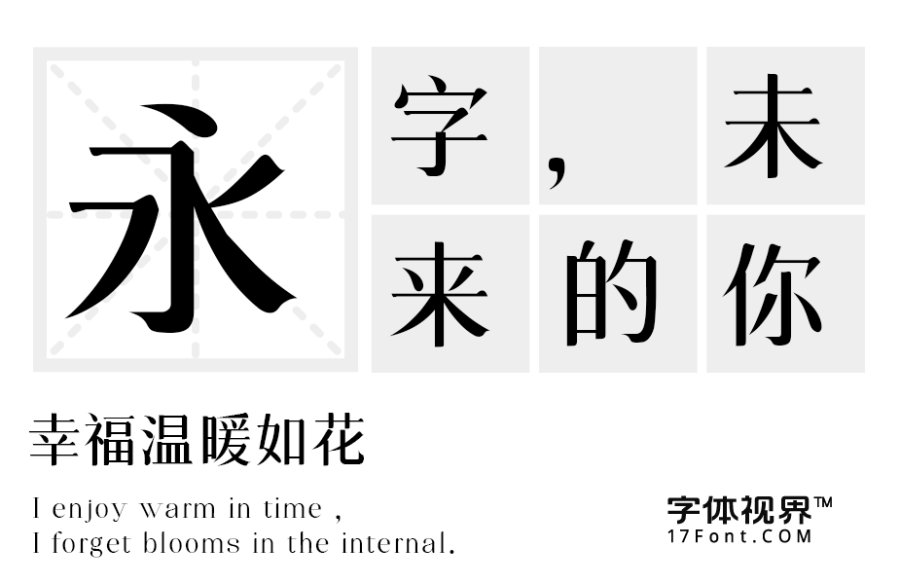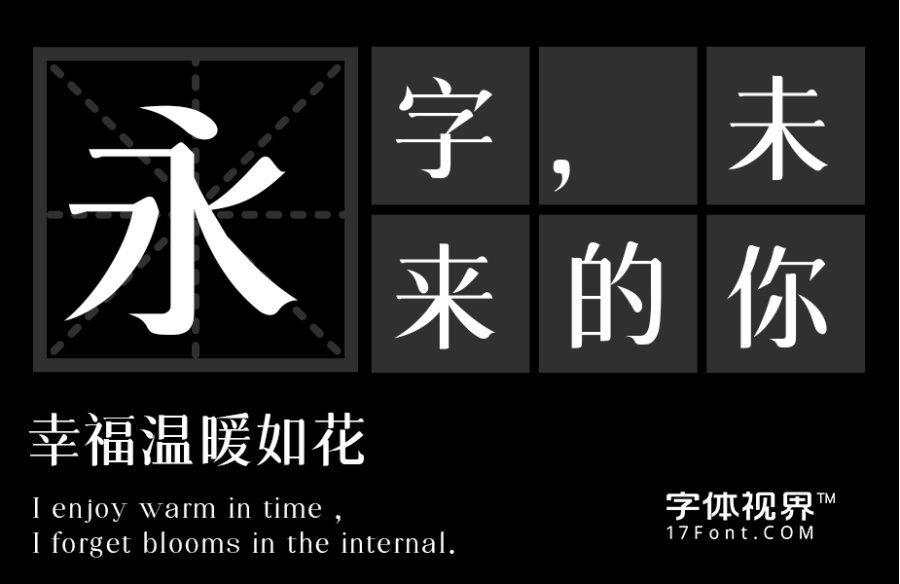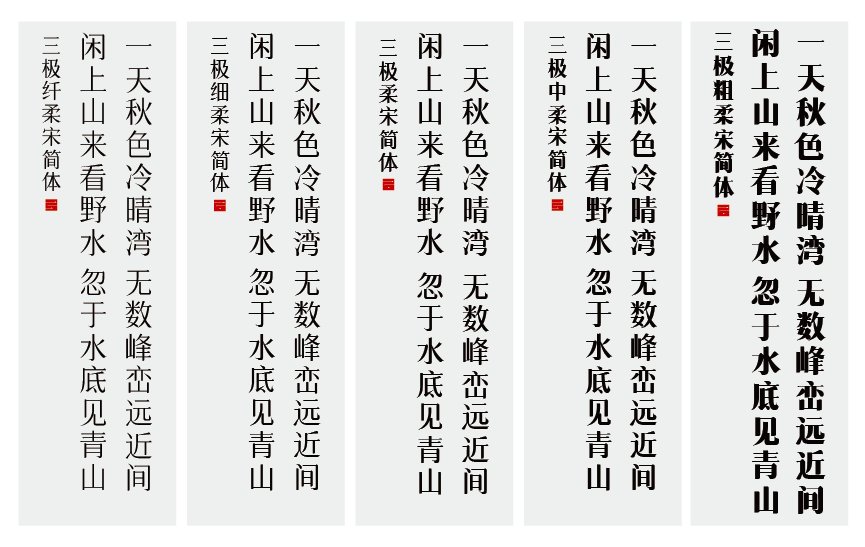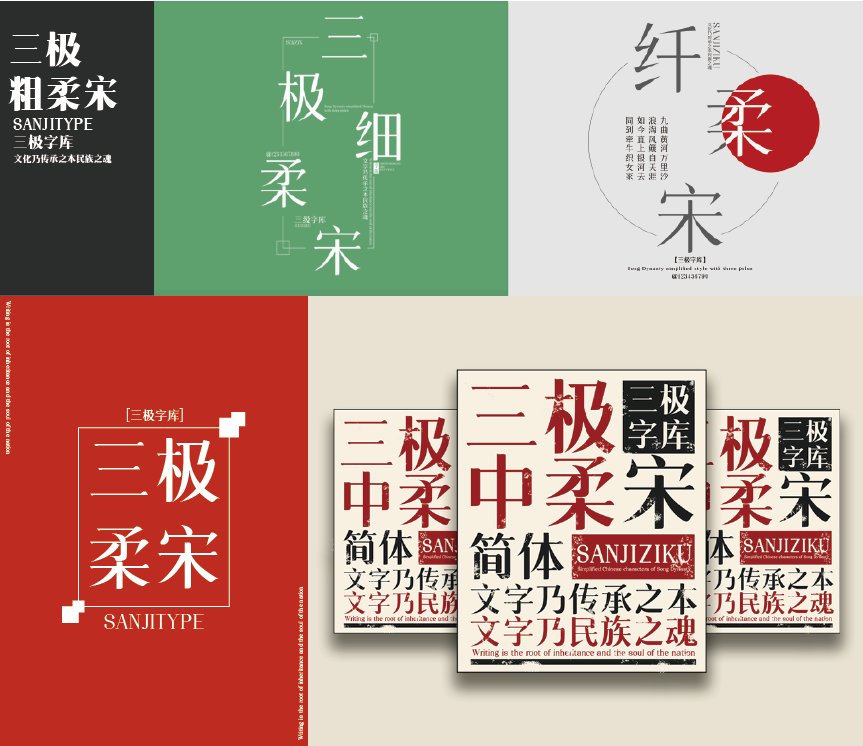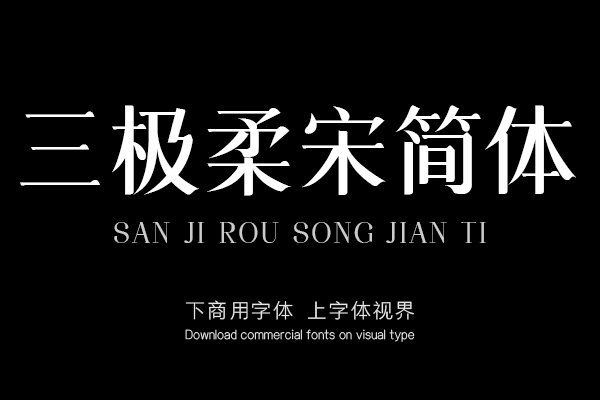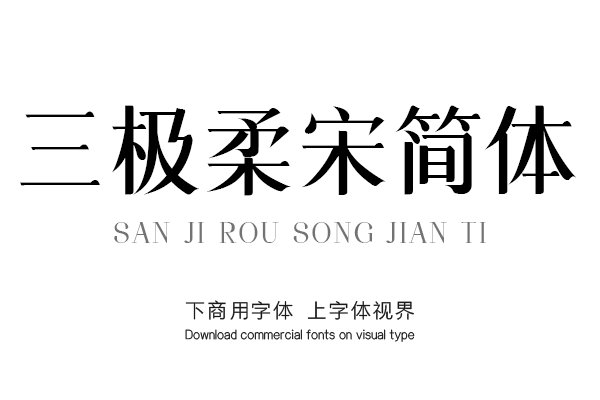
三极柔宋简体是一款家族字体,其字形清新,布白均匀,字形结构饱满匀称、柔美,中宫偏大,笔形挺拔流畅,笔锋锐利简洁。撇、捺起笔收笔统一,个性鲜明,富有朝气。这款字的......购买须知:“下载服务费”与“字体VIP”所获得字体 仅用于个人非商用, 商用请联系付费授权。本字体为电脑用字,手机没有root权限不支持直接手机换字(手机如何root,请自行百度搜索教程)。购买前请先 了解清楚后再付款 ,字体为虚拟产品无法回收 一旦购买不支持退款。